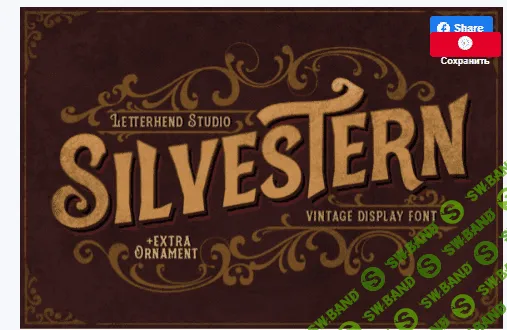
Название: Silvestern Font (2021)
Silvestern - это крутой, жирный шрифт в винтажном стиле. Добавьте этот напористый шрифт к своим любимым дизайнам и обратите внимание, как они мгновенно оживают.